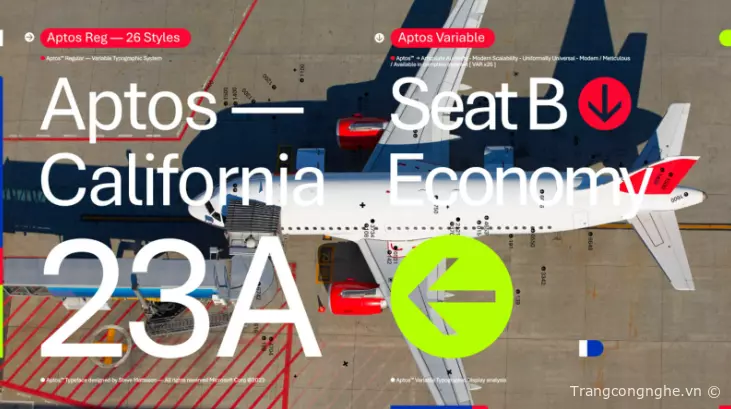
Microsoft Office thay đổi font chữ mặc định sau 15 năm sử dụng Calibri
Microsoft Office đã chính thức sử dụng Aptos làm font chữ mặc định cho các bộ ứng dụng Office. Đây là lần đầu tiên Microsoft thay đổi font chữ mặc định trong Office kể từ năm 2007, khi họ chuyển từ Times New Roman sang Calibri.
Trước đó, vào năm 2021, Microsoft đã chọn 5 font chữ bao gồm: Bierstadt, Grandview, Seaford, Skeena và Tenorite để người dùng lựa chọn và góp ý. Mỗi font đều có những đặc điểm riêng, từ hình dạng chữ cái đến khoảng cách giữa các ký tự. Sau nhiều năm, Aptos (được đổi tên từ Bierstadt) là font chữ được nhiều người dùng yêu thích nhất và nó sẽ là font chữ mặc định cho các bộ ứng dụng Office của hãng.
Aptos là một font chữ sans-serif được thiết kế bởi một nhóm các nhà thiết kế tại Microsoft. Font chữ này được lấy cảm hứng từ font chữ Segoe UI, font chữ mặc định của Windows. Aptos được thiết kế để có độ dễ đọc cao, đặc biệt là trên các thiết bị màn hình nhỏ. Font chữ này cũng có nhiều tính năng linh hoạt, cho phép người dùng tùy chỉnh kích thước, màu sắc và khoảng cách giữa các ký tự.
Việc Microsoft sử dụng Aptos làm font chữ mặc định cho các bộ ứng dụng Office là một sự thay đổi lớn. Font chữ này được thiết kế để phù hợp với nhu cầu sử dụng của người dùng trong thời đại kỹ thuật số. Aptos là một font chữ hiện đại, dễ đọc và linh hoạt, chắc chắn sẽ được nhiều người dùng yêu thích.
Microsoft đã chính thức thay đổi font chữ mặc định cho các bộ ứng dụng Office từ Calibri sang Aptos. Đây là một sự thay đổi lớn, được thiết kế để tạo ra một trải nghiệm mới cho người dùng, phù hợp với xu hướng thiết kế hiện đại và đa dạng.
Aptos là một font chữ sans-serif được thiết kế bởi Steve Matteson, một nhà thiết kế kiểu chữ nổi tiếng. Font chữ này được lấy cảm hứng từ font chữ Segoe UI, font chữ mặc định của Windows. Aptos được thiết kế để có độ dễ đọc cao, đặc biệt là trên các thiết bị màn hình nhỏ. Font chữ này cũng có nhiều tính năng linh hoạt, cho phép người dùng tùy chỉnh kích thước, màu sắc và khoảng cách giữa các ký tự.
Việc Microsoft sử dụng Aptos làm font chữ mặc định cho các bộ ứng dụng Office là một phần trong chiến lược của Microsoft nhằm giúp Microsoft 365 trở nên toàn diện và hiện đại hơn. Font chữ này được thiết kế để phù hợp với nhu cầu sử dụng của người dùng trong thời đại kỹ thuật số. Aptos là một font chữ hiện đại, dễ đọc và linh hoạt, chắc chắn sẽ được nhiều người dùng yêu thích.
Dưới đây là một số lợi ích của việc sử dụng Aptos làm font chữ mặc định cho các bộ ứng dụng Office:
• Aptos có độ dễ đọc cao, đặc biệt là trên các thiết bị màn hình nhỏ.
• Aptos có nhiều tính năng linh hoạt, cho phép người dùng tùy chỉnh kích thước, màu sắc và khoảng cách giữa các ký tự.
• Aptos là một font chữ hiện đại, phù hợp với xu hướng thiết kế hiện đại và đa dạng.
• Aptos là một font chữ dễ đọc và linh hoạt, chắc chắn sẽ được nhiều người dùng yêu thích.